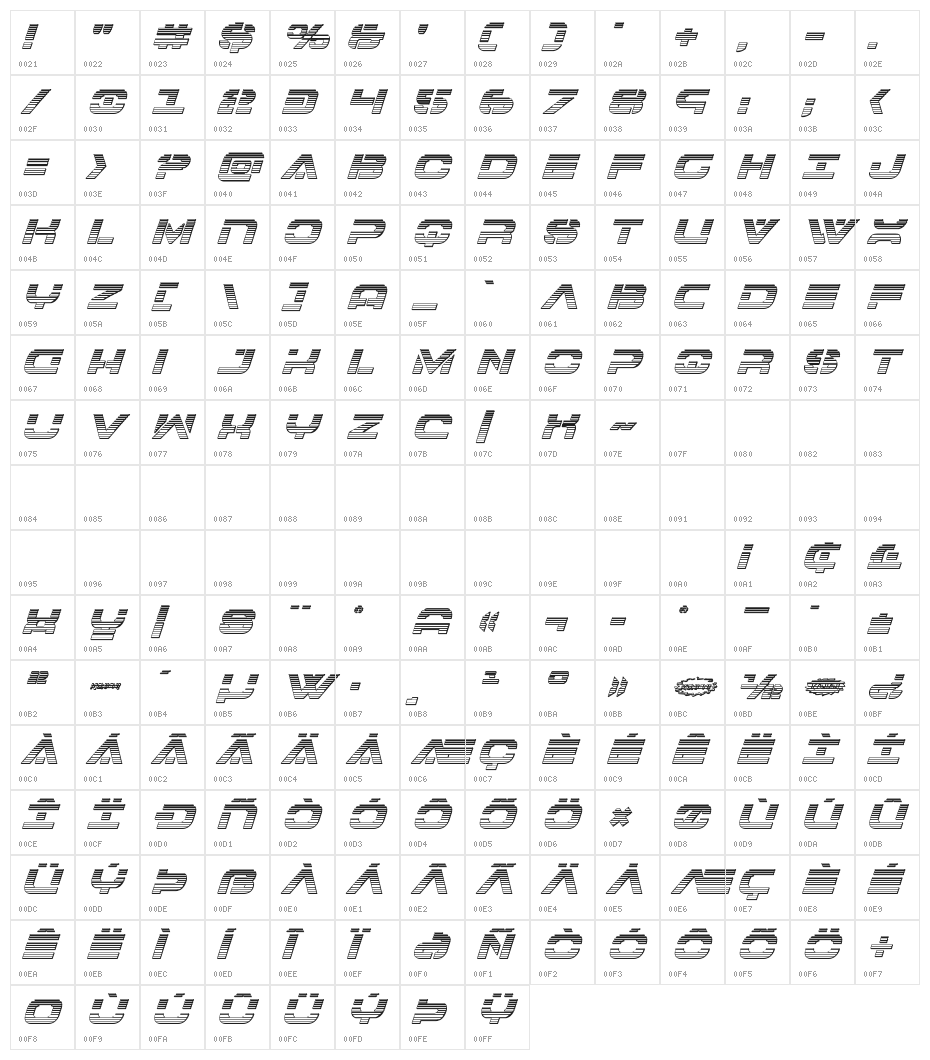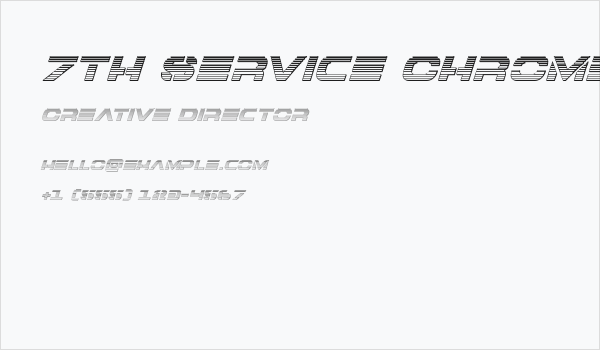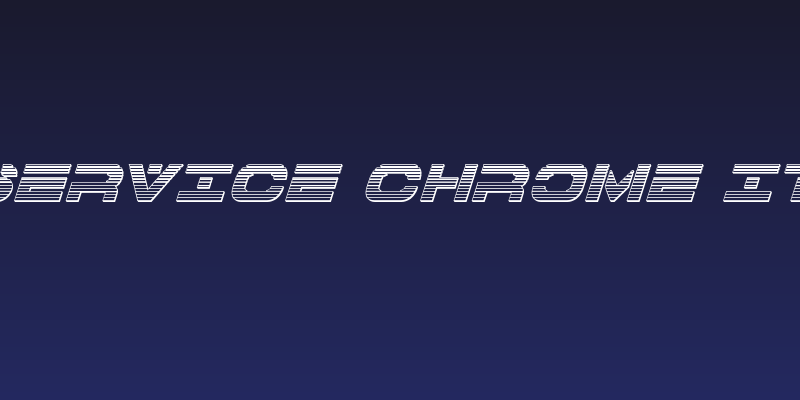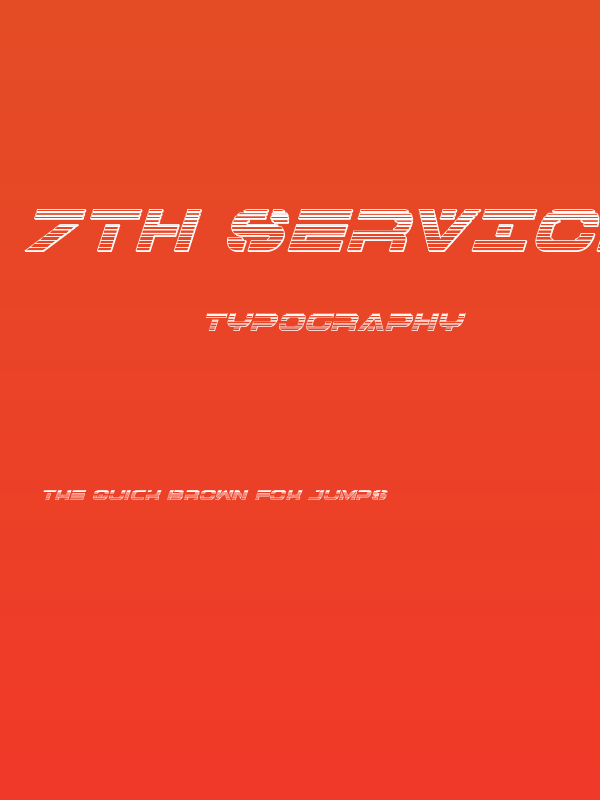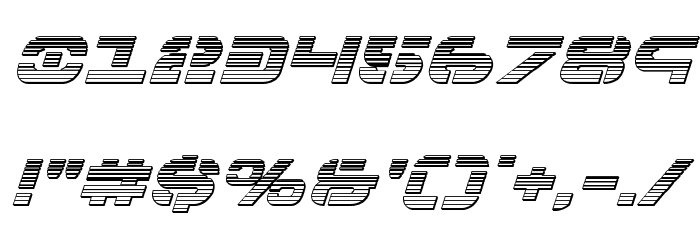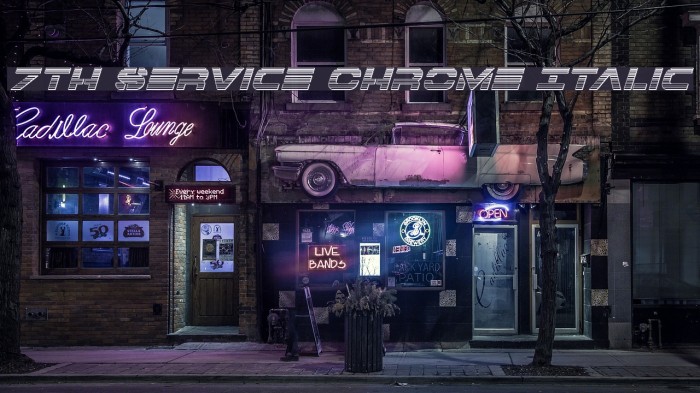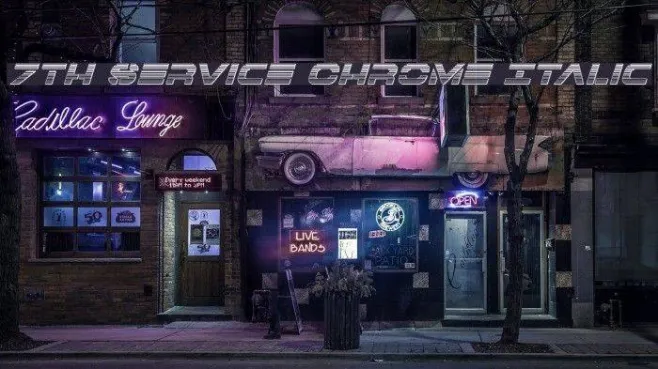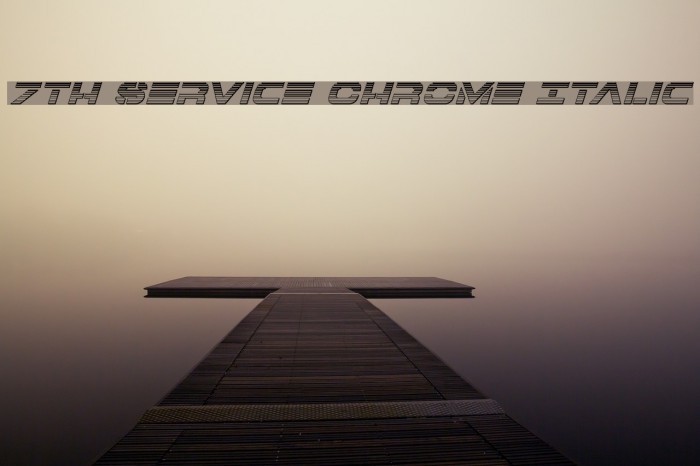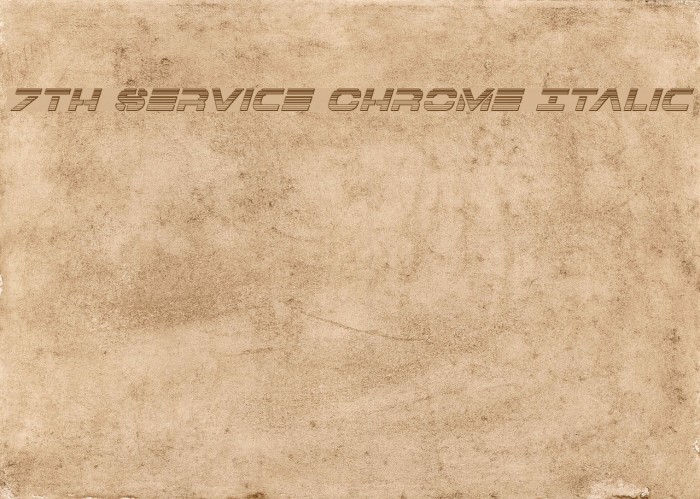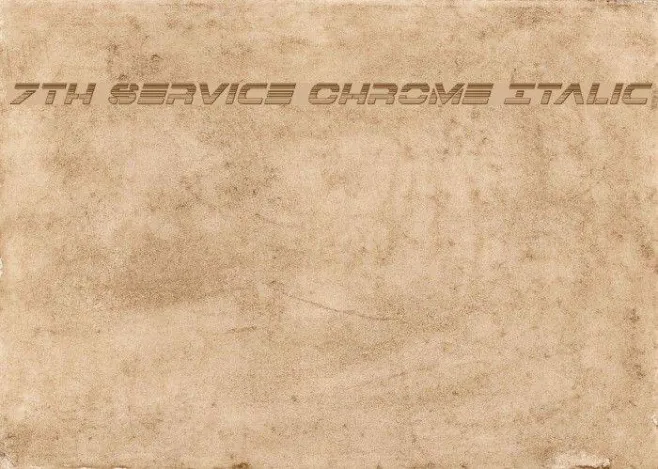
7th Service Chrome Italic Font
| Proyectos propuestos | Ideal for technology branding, automotive advertisements, sports team logos, and futuristic-themed posters. |